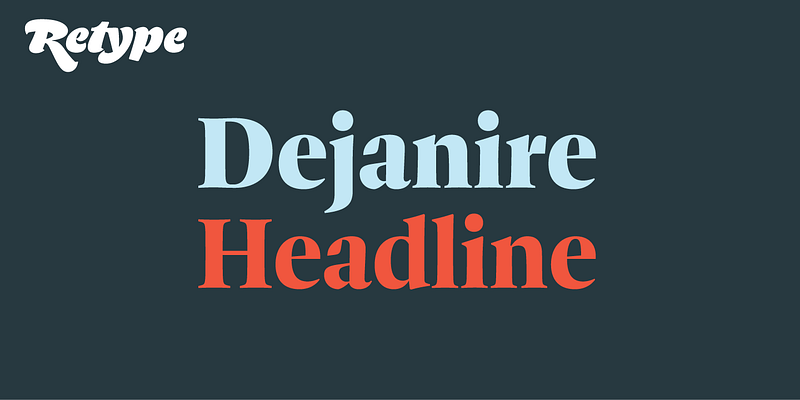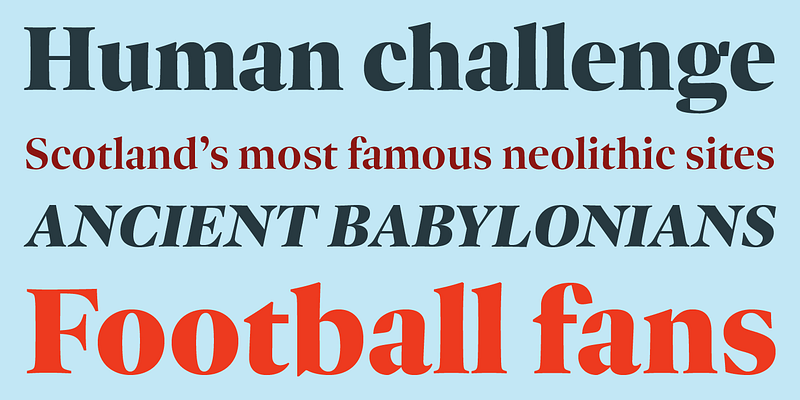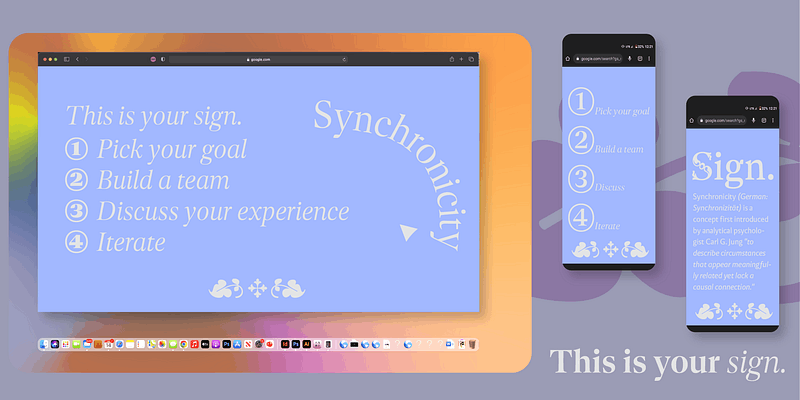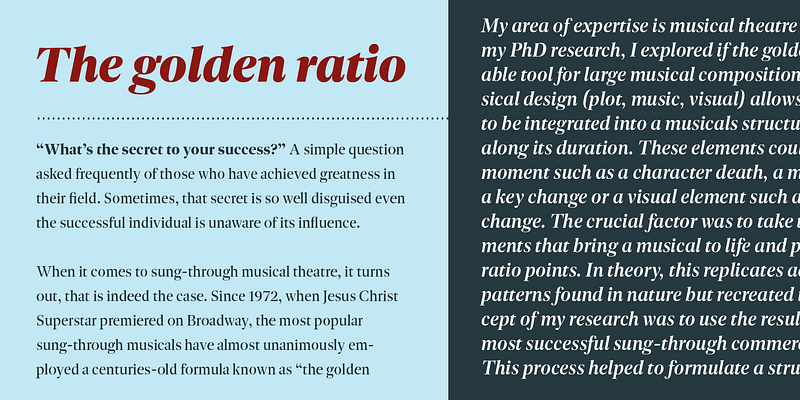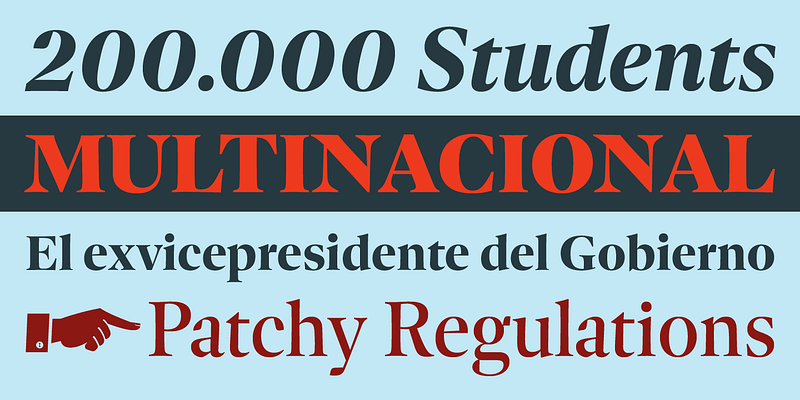
Dejanire est une famille de caractères librement inspirée d’une police d’affichage anonyme trouvée dans un spécimen de caractères de Claude Lamesle, publié à Paris en 1742. Elle tire son nom de Deianira, une princesse calydonienne et l’épouse d’Héraclès dans la mythologie grecque. Le Dejanire est une police romaine aux formes transitoires, avec un contraste marqué et une présence nette, à la fois à l’impression et à l’écran, ce qui en fait un choix idéal pour les gros titres, les citations phares et les ponts.